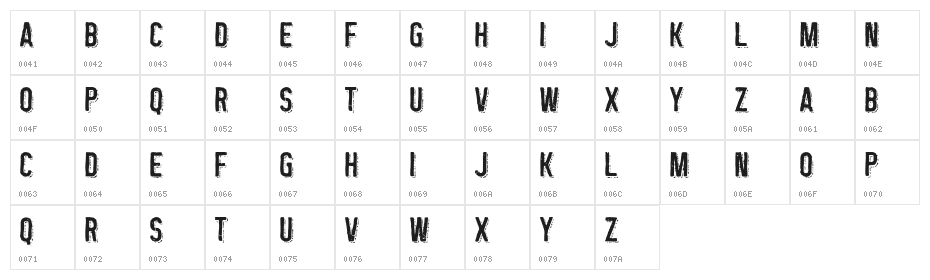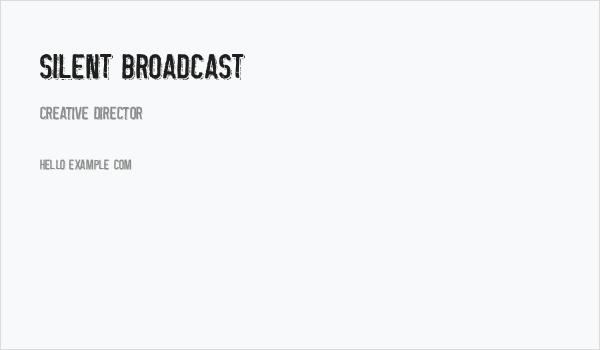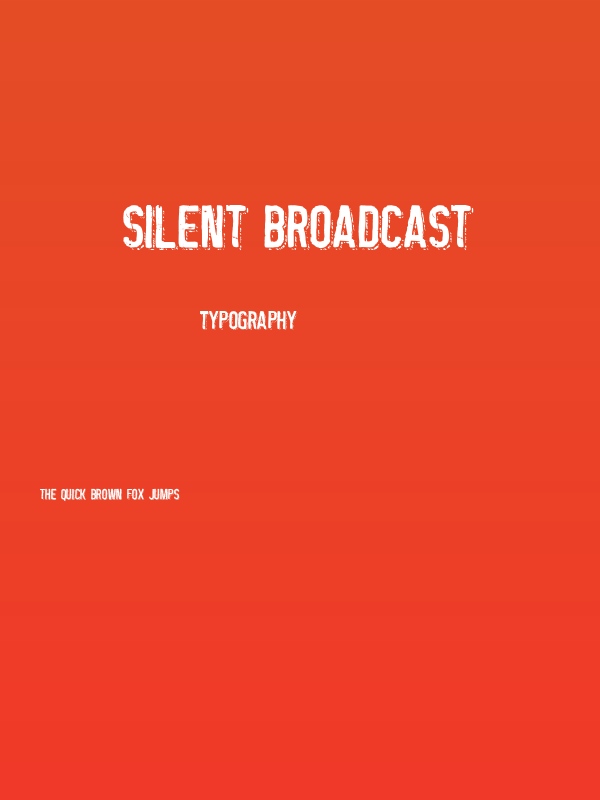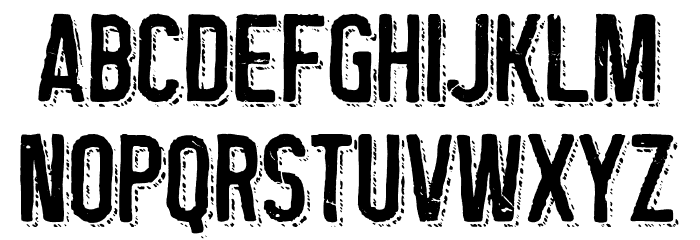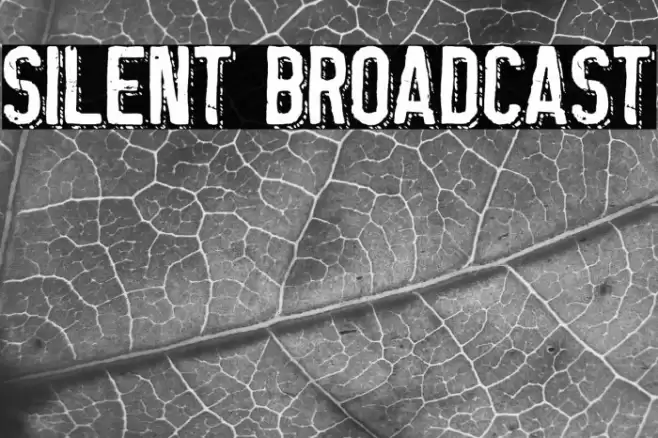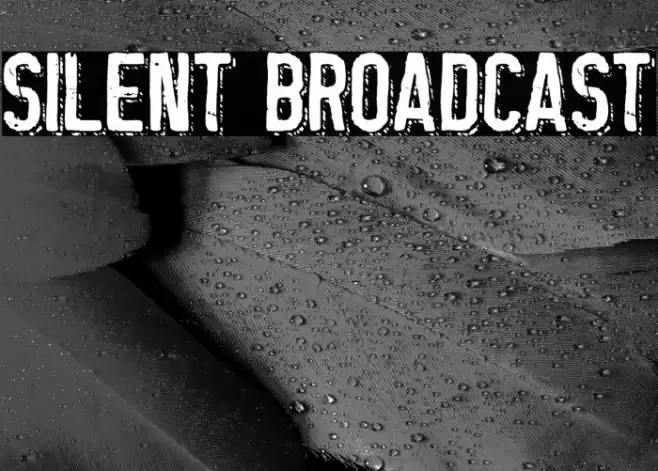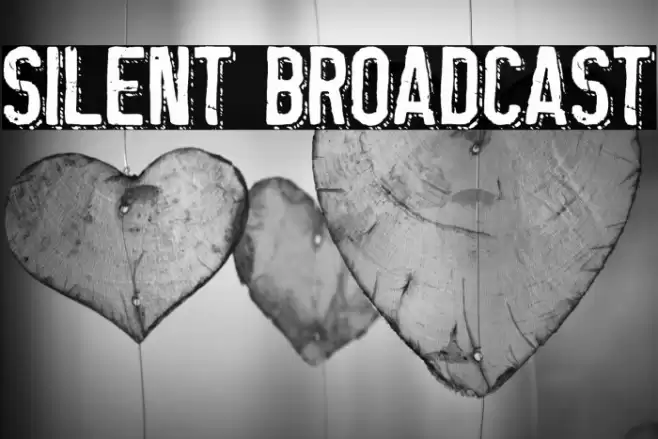
Silent Broadcast Font
✎ Messy
| Gesamtstil | Vintage |
| Vorgeschlagene Projekte | Ideal for vintage posters, retro-themed branding, rustic signage, and attention-grabbing headlines. |